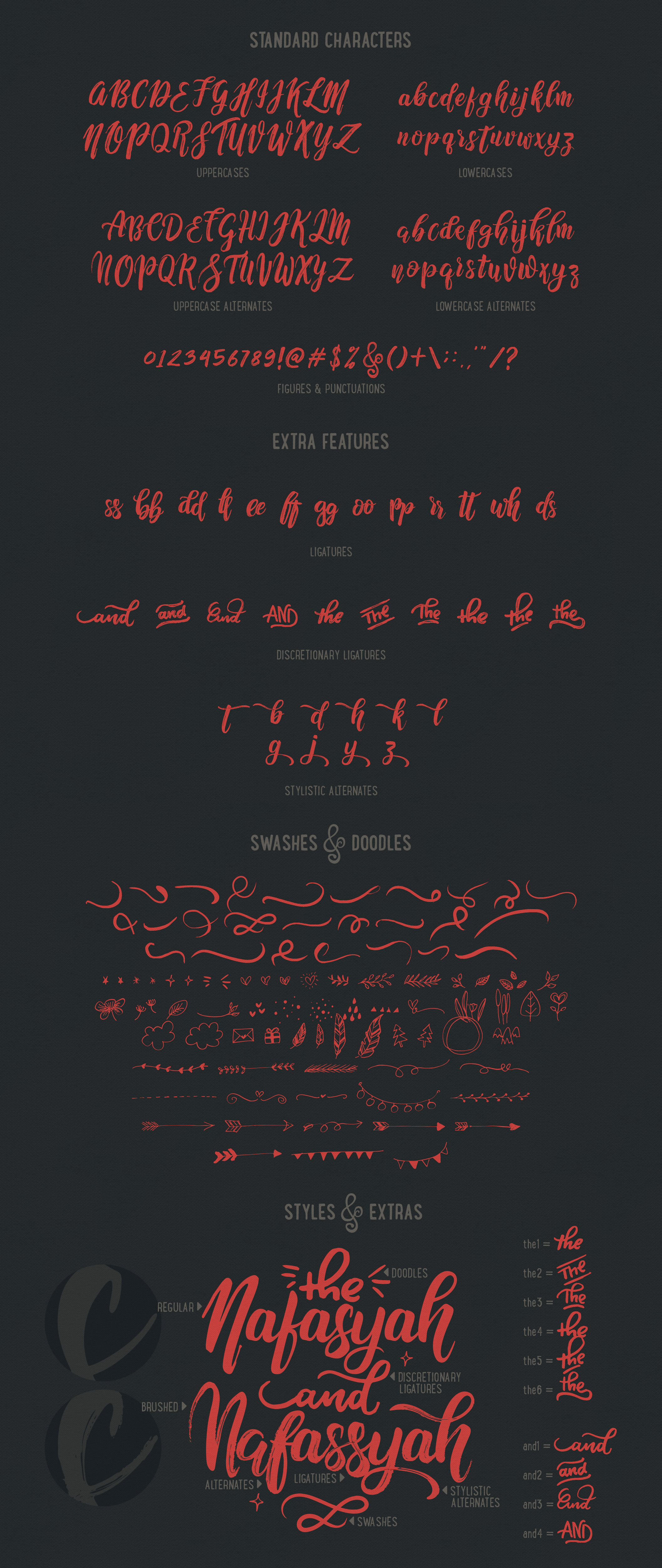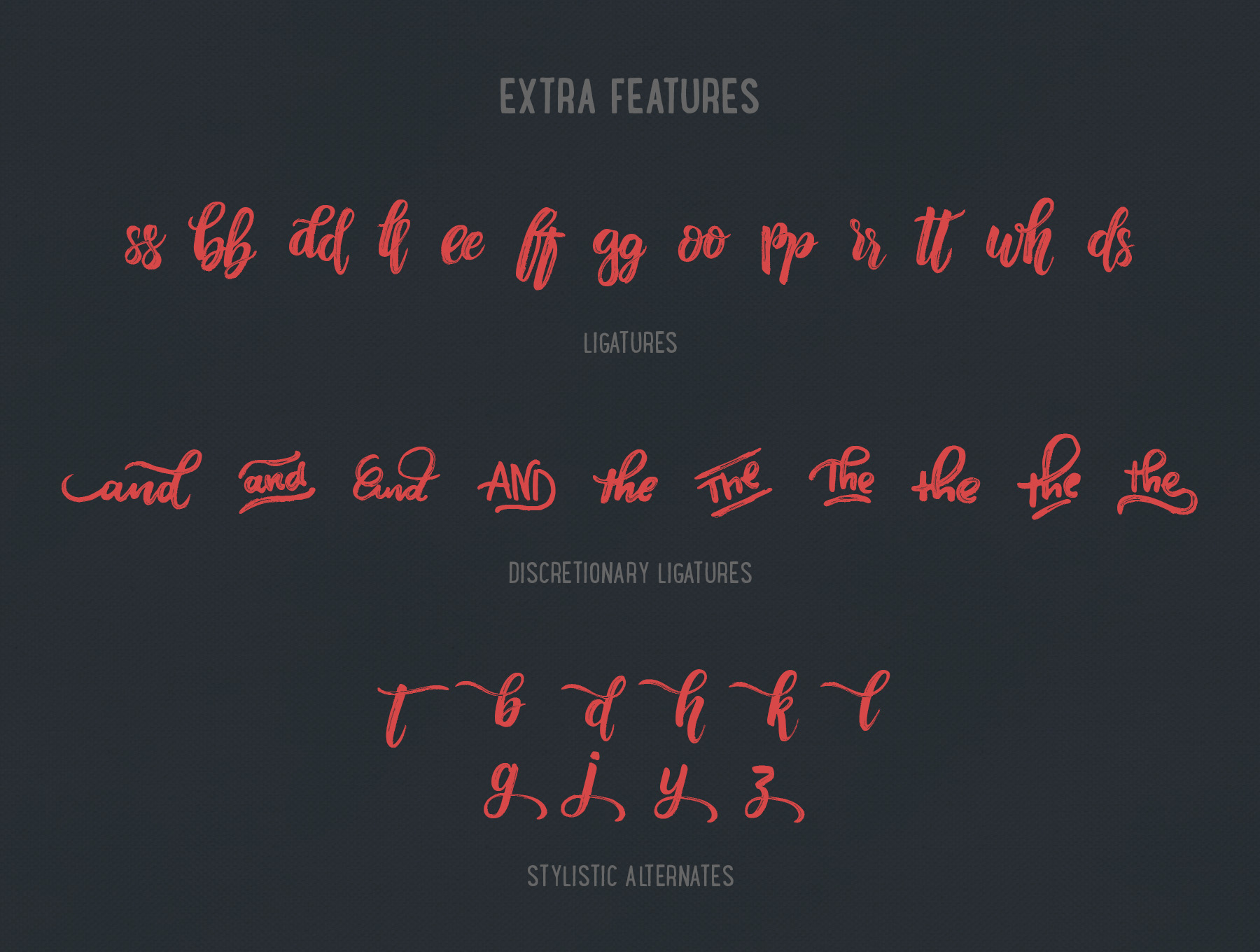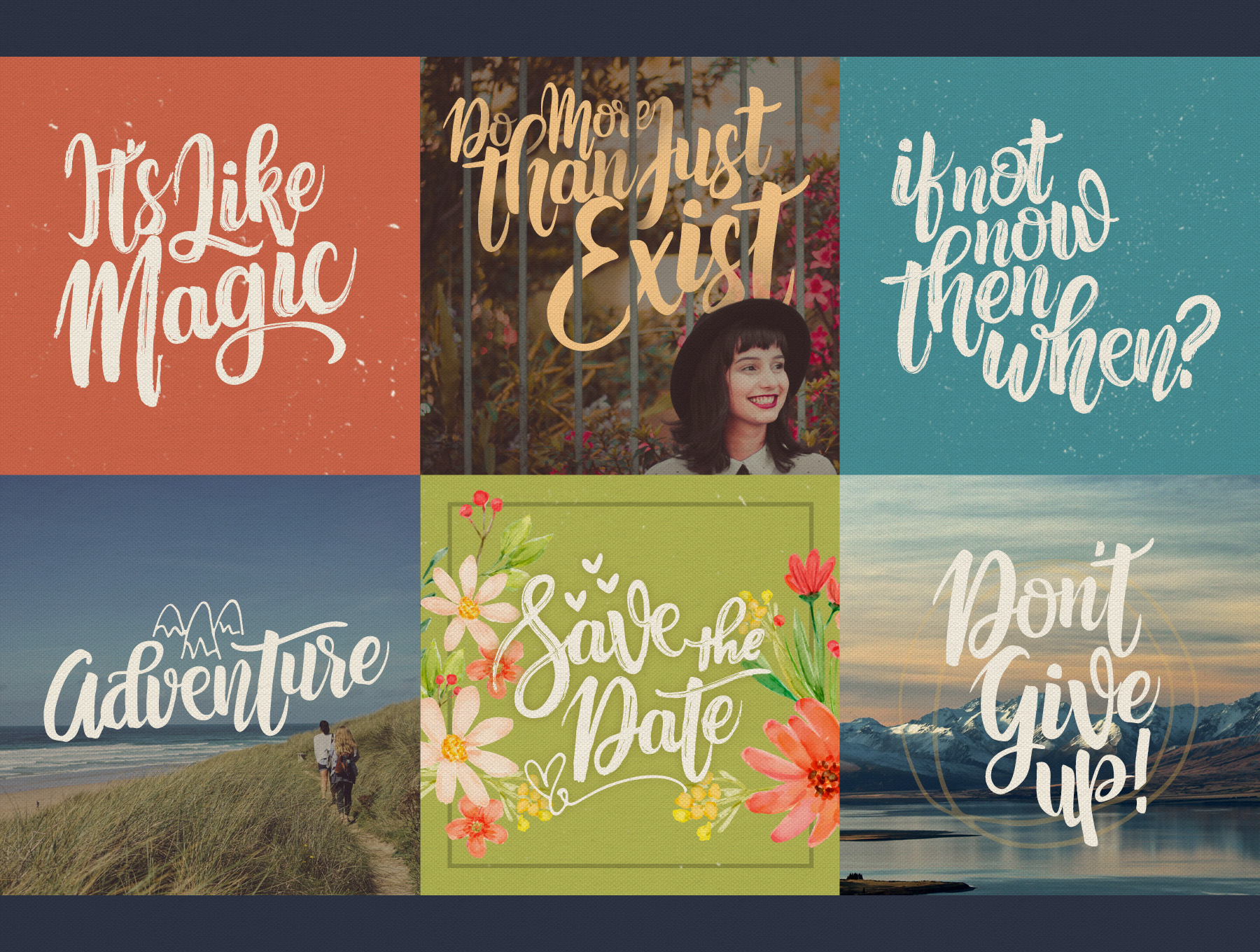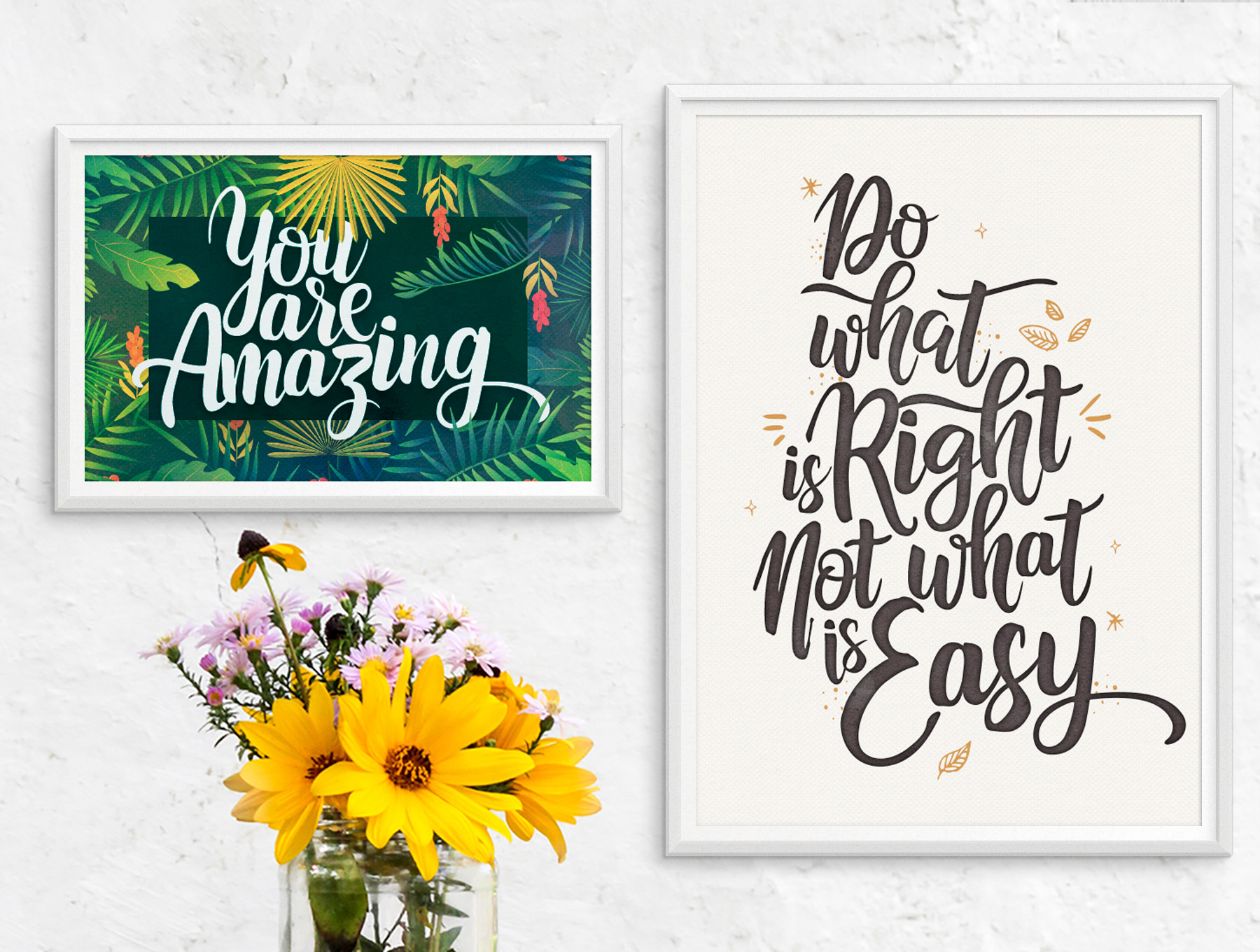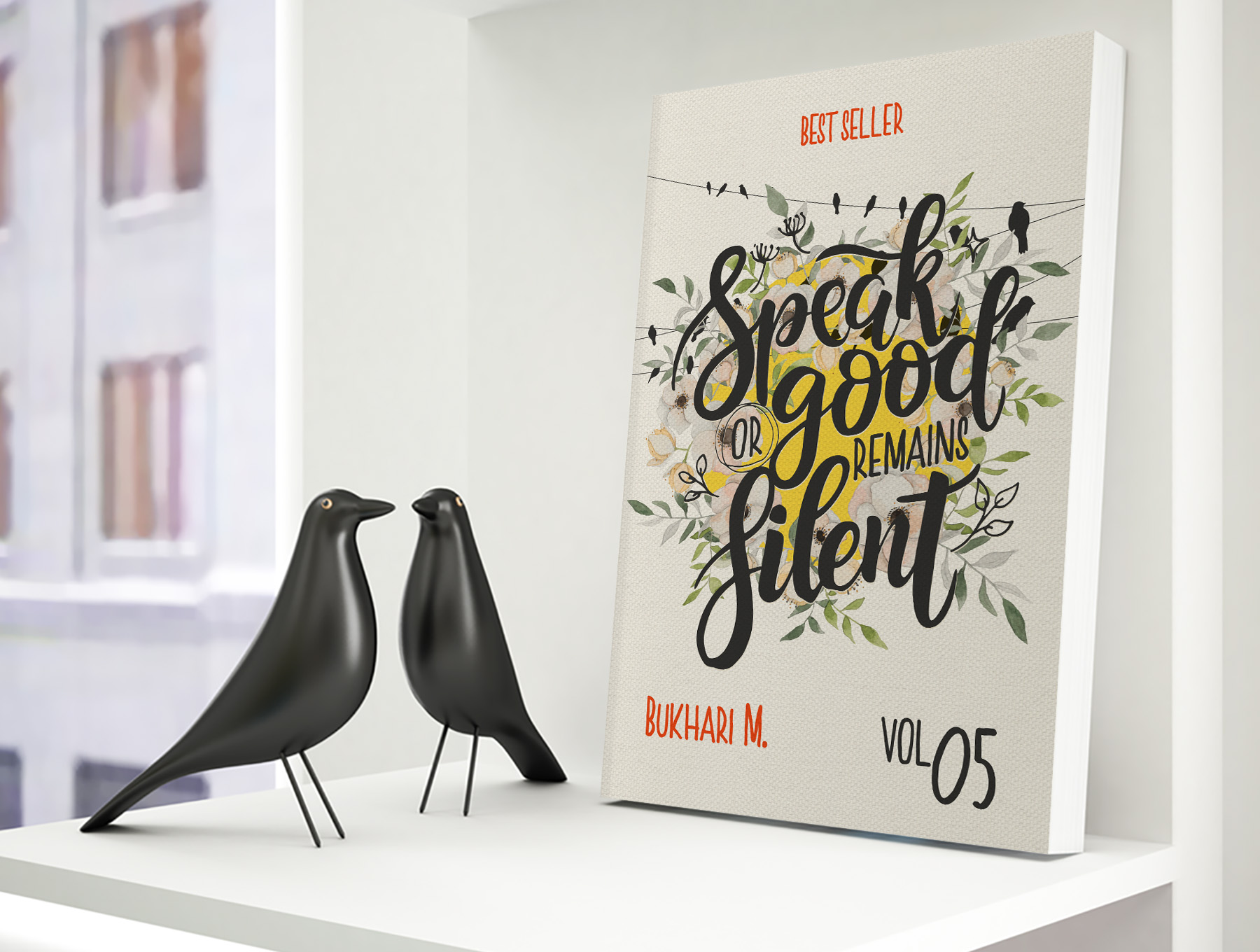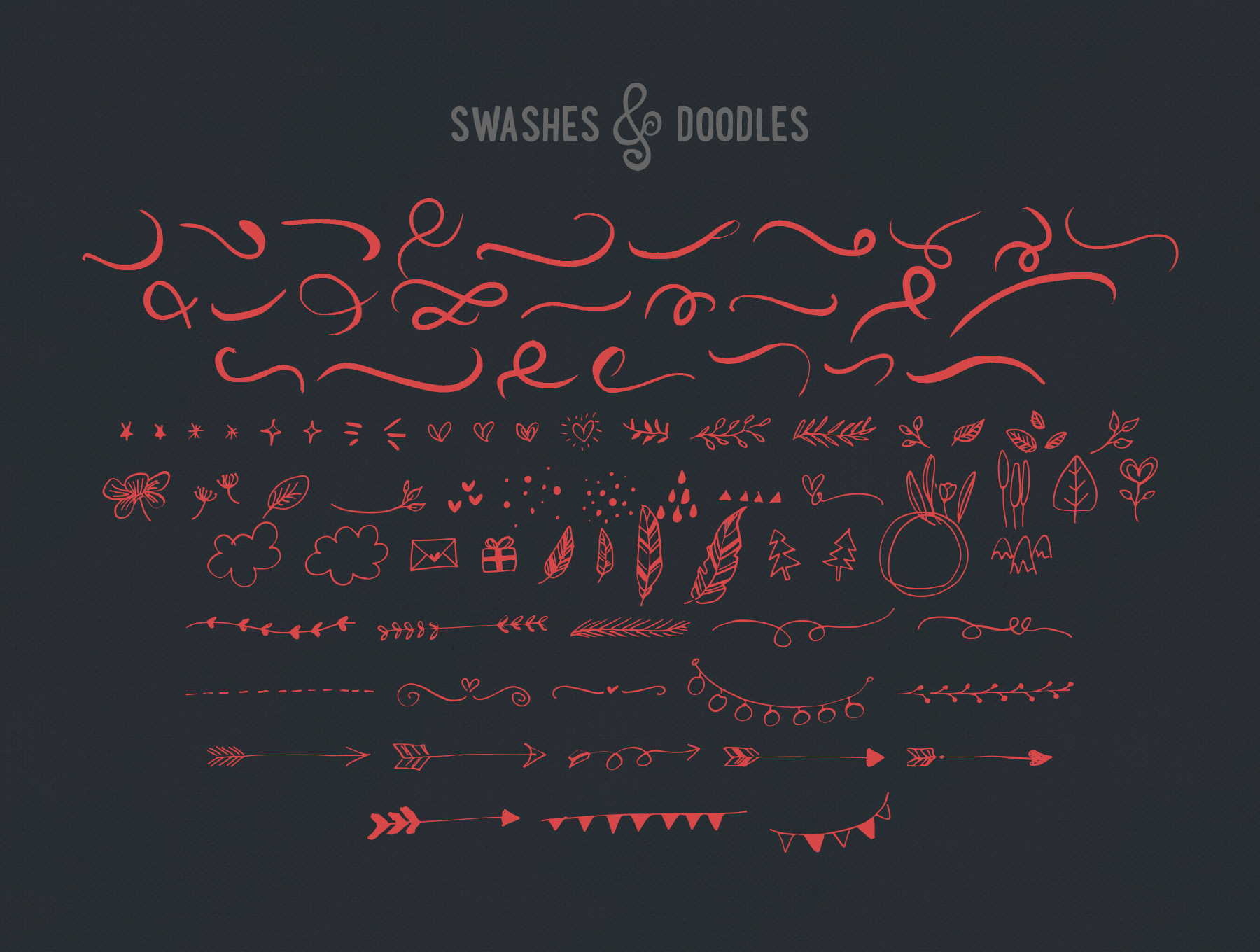
拉丝字体二重奏,Nafasyah
Brushed Font Duo, Nafasyah
一套完整的手工字母字体,为您精彩的文字和精美的艺术品提供个性化的触感。 Nafasyah更新版本附带常规,拉丝,无衬里和额外(花饰+涂鸦)版本。结合Nafasyah Extra,您将获得花饰和涂鸦来装饰您的作品。
使用Discretionary ligatures,您只需要在单词“and”和“the”的末尾添加数字字符。例如,您可以键入and1,and2,and3或and4来显示“和”连字。或者只需键入1,the2,the3,the4,the5或the6即可显示“the”连字。太有趣了!